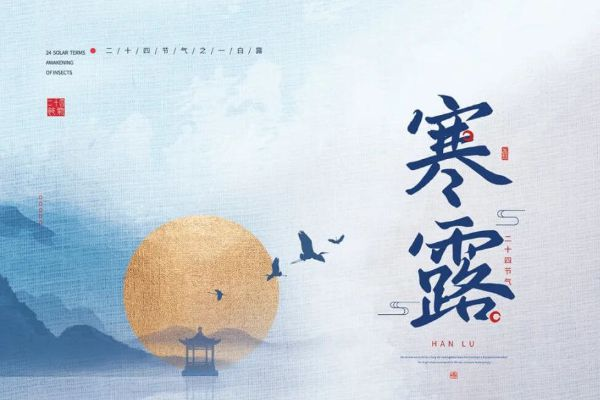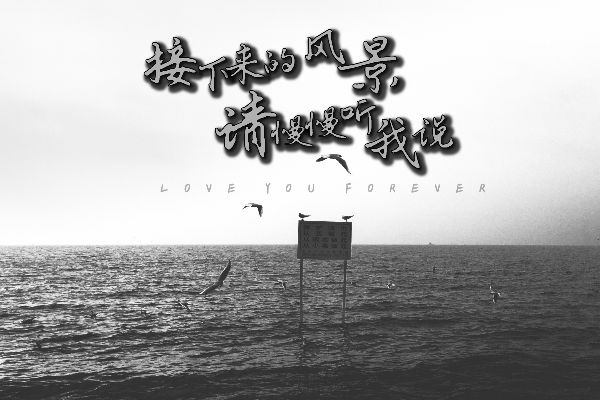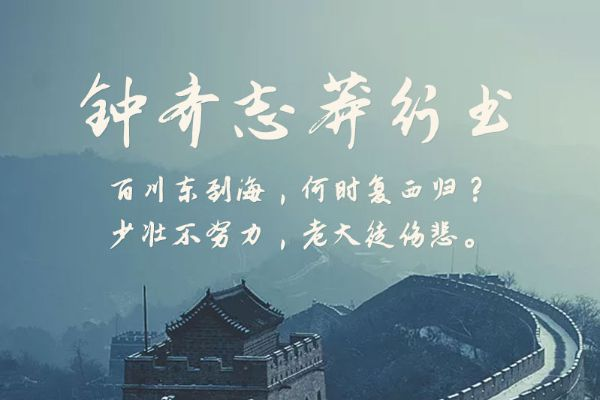
行书字体大全,四款免费商用的行书字体以及三个授权字库
作为一名从事设计工作多年的创作者,我对行书字体有着特殊的情感。这种介于楷书和草书之间的字体,既保留了传统书法的韵味,又不失实用性,在我的项目中经常用到。今天我想和大家分享一下一些我常用的行书字体,以及哪些可以免费商用、哪些需要授权。
行书字体的特点
行书的笔画之间有明显的连接,写起来比楷书快,但又不像草书那样难以辨认。这种特性让它特别适合用在需要传达人文气息的设计场景中。我做过一个茶叶品牌的包装设计,客户要求既要有文化底蕴,又不能太过艰涩,最后选用行书字体就达到了很好的效果。
从结构上看,行书可以分为行楷和行草两类。行楷更接近楷书,笔画虽有连带但整体工整;行草则更随性,笔意更浓,艺术感更强。我在实际工作中,如果是做正式一些的商务场合材料,会选择行楷;如果是文化类、艺术类的项目,行草会是更好的选择。
我常用的免费商用行书字体
鸿雷行书
鸿雷行书是一款笔势流畅、气韵生动的行书字体。这款字体笔画连贯自然,结构灵活多变,展现出行云流水般的书写韵律。字形洒脱大气,具有较强的艺术感染力。适合书法作品、文化海报、品牌标识等需要体现书法艺术美感的设计场景。
立即下载行书字体云峰静龙行书
云峰静龙行书是一款兼具静谧与力量的行书字体。字体在保持行书流动特征的同时,注重笔画的控制和结构的平衡,呈现出内敛而有力的气质。适合高端品牌设计、文化艺术项目、茶酒包装等需要展现深厚文化底蕴的应用场景。
钟齐志莽行书
钟齐志莽行书是钟齐字库推出的一款个性鲜明的行书字体。字体笔势奔放、线条粗犷,展现出率性洒脱的气质。适合创意海报、艺术展览、个性品牌、文创产品等需要突出个性和艺术感的设计应用。
濑户字体
这是一款日本设计师开发的免费字体,支持中文。它的笔触有手写感,虽然不是严格的行书,但那种自然流畅的风格很接近行书的气质。我在做一些轻松活泼的项目时会选它,比如咖啡店的菜单设计、文创产品的文案排版。
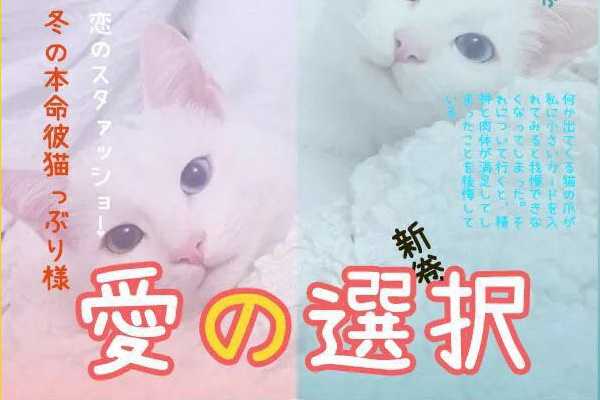
值得购买授权的行书字体
汉仪字库的行书类字体也很出色,比如汉仪雅酷黑、汉仪尚巍手书等。我特别喜欢汉仪尚巍手书,它是设计师尚巍的手写字体,每个字都带着温度。我给一家独立书店做过品牌设计,全套VI都用了这款字体,营造出了很好的文艺气息。
华康字库
华康是台湾知名的字体品牌,旗下有华康POP1体、华康雅宋体等。华康的字体设计比较活泼,笔画处理上能看到行书的灵动感。我在做一些快消品包装设计时会用到,特别是食品类的项目,华康字体那种轻松愉悦的感觉很合适。
文悦古典明朝体、文悦新青年体等都是我很喜欢的字体。文悦的字体在传统书法和现代设计之间找到了很好的平衡点。我给一家高端酒店做过导视系统设计,就用了文悦古典明朝体,既体现了酒店的格调,又保证了识别性。
行书在使用中的技巧
场景匹配
行书字体自带文化属性,更适合传统文化、茶酒、文创、教育等领域。我曾经在一个科技公司的项目中误用了过于传统的行书字体,结果客户觉得和品牌调性不符。后来我换成了偏现代的、只是带有行书笔意的字体,问题就解决了。
字号和行距
行书字体的笔画比较复杂,如果字号太小,笔画容易糊在一起,影响识别。我一般在正文排版时不会用纯行书字体,而是用在标题、引语这些大字号的地方。如果必须用在正文,我会适当增加行距和字距,保证阅读舒适度。
颜色选择
行书字体本身已经很有特色了,我在设置颜色时会比较保守。黑色、深灰色是最安全的选择;如果要用彩色,我会选择饱和度较低的颜色,比如墨绿、深蓝、褐色等,这样才能和行书的文化气质相匹配。